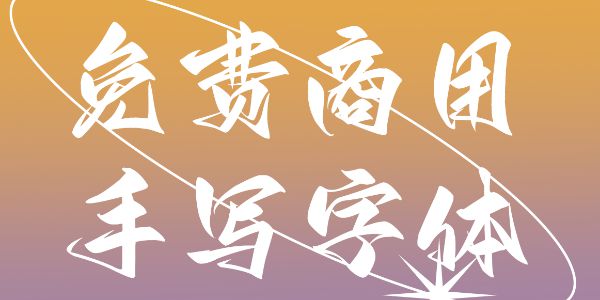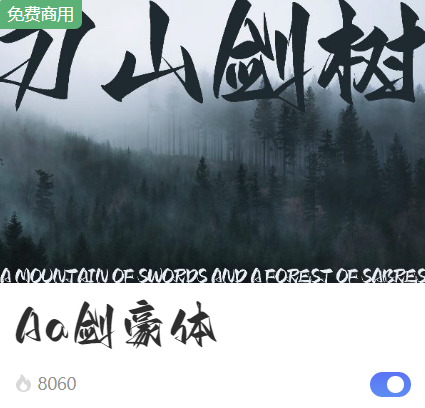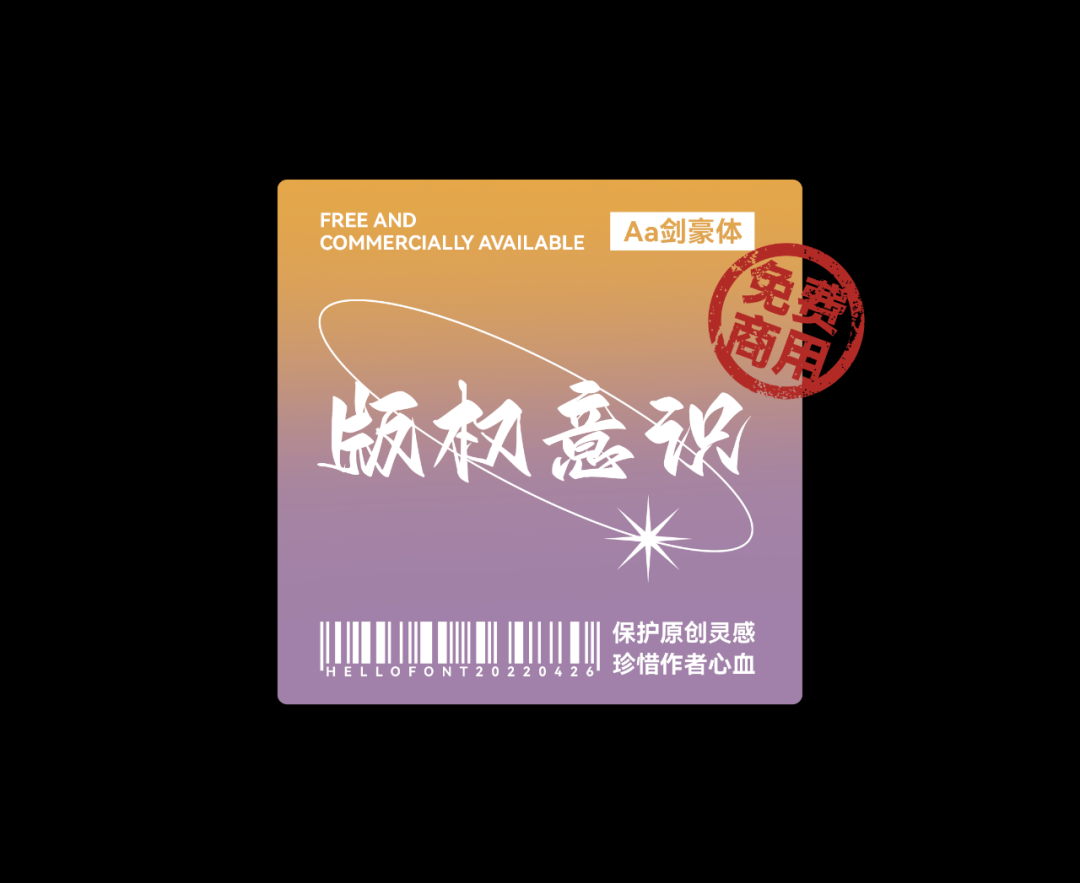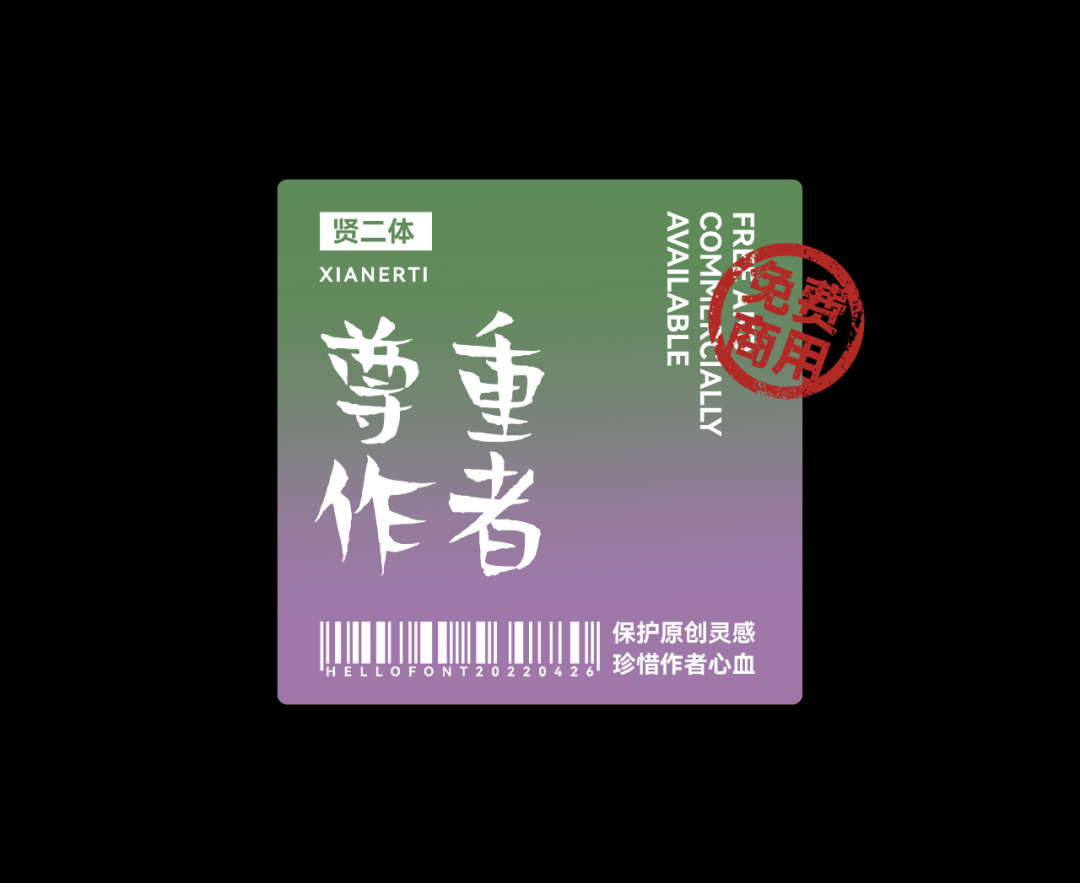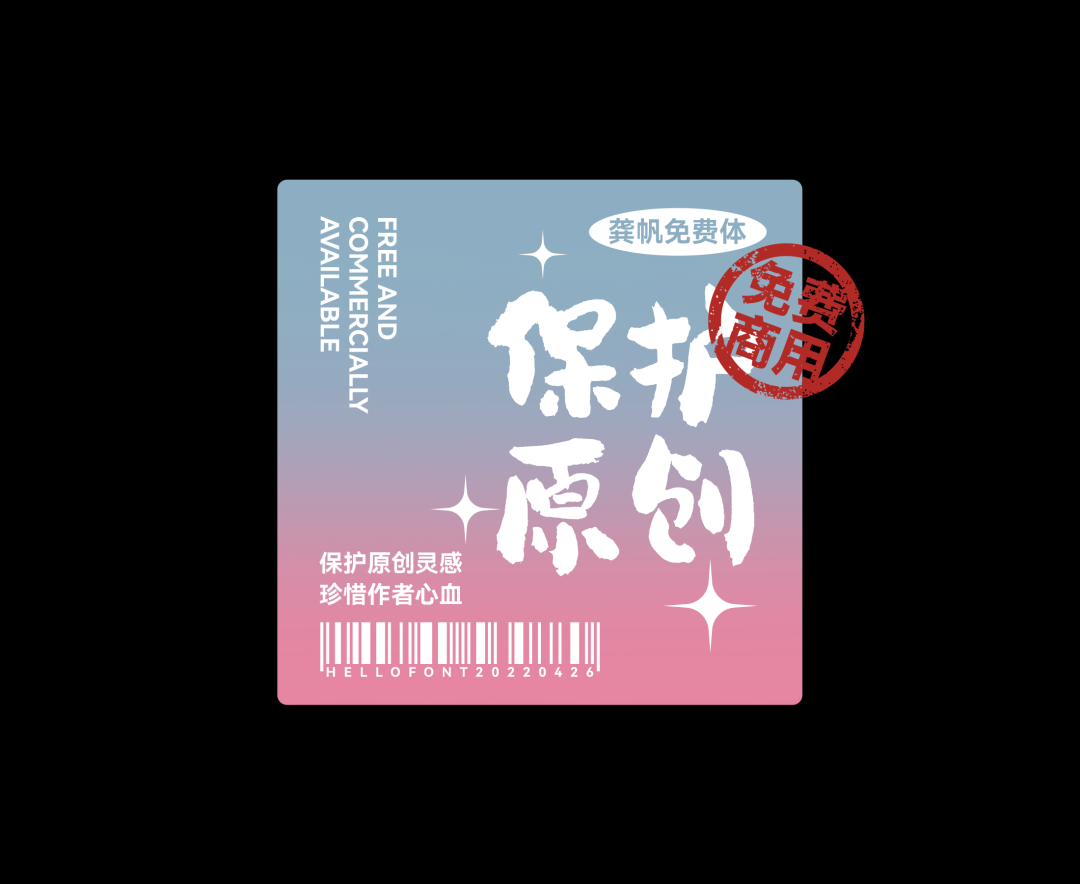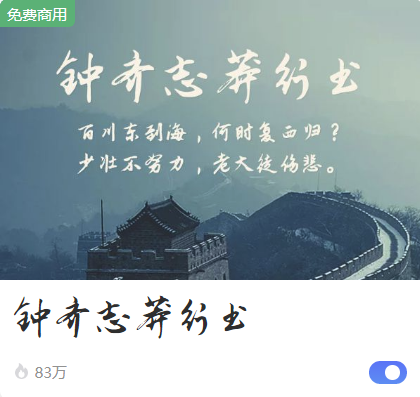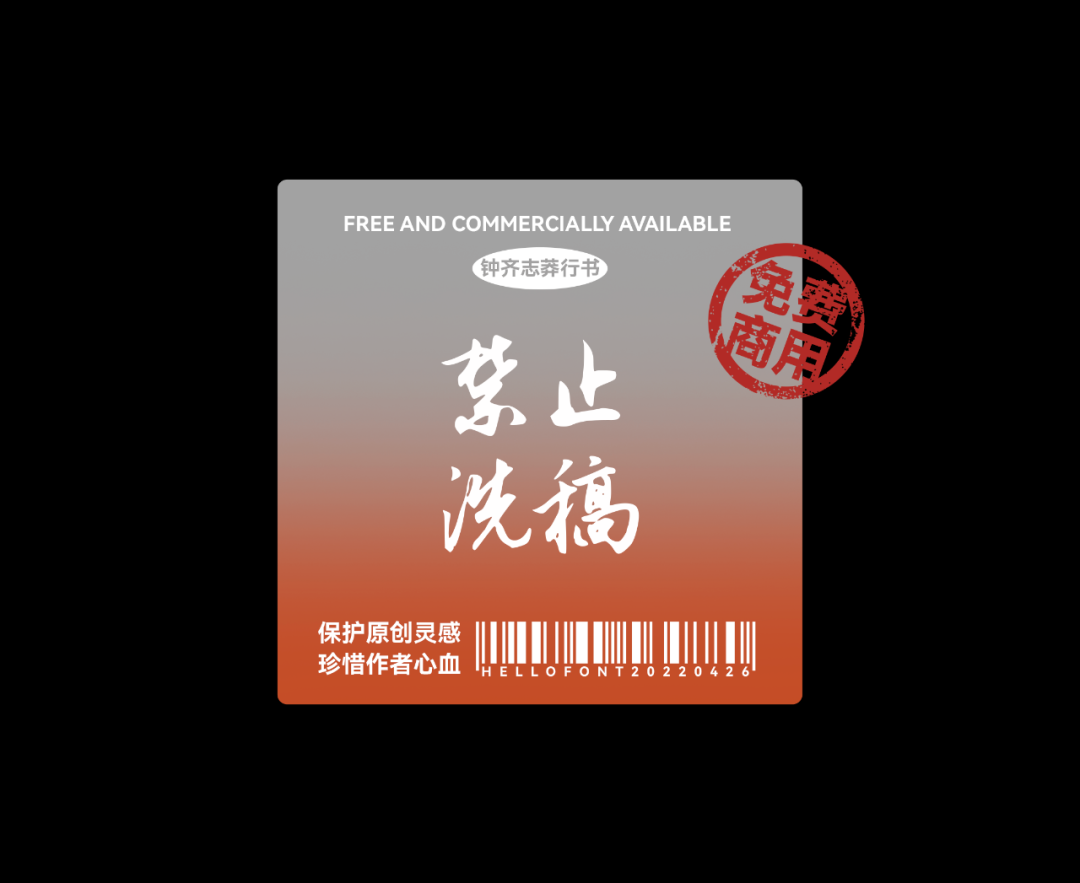
有了这些免费字体,走到哪我都不慌~
01
Aa剑豪体
AaJianHaoTi
Aa字库大家一定不陌生,字由上也有很多它的字体。
如果你既不是字由会员,也不想单独授权,那你今天一定要码住了,因为它们出了首款免费商用字体
还是你们最爱的手写体,一笔一划间都透着洒脱、豪放的气质。
当然,一款肯定不够用,所以柚子又找了其它几款手写体,看看有没有你用过的?
02
贤二体
XianErTi
03
龚帆免费体
gongfanmianfeiti
04
钟齐志莽行书
ZhiMangXing
05
鸿雷板书简体
HongLeiBanShuJ